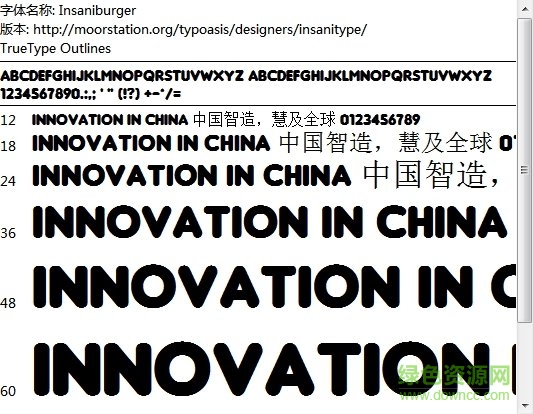
insaniburger字體是一款有著極佳視覺呈現(xiàn)的英文字體,自帶加粗加黑設(shè)計,讓英文文字更加深入人心,有著不錯的第一印象,給你的設(shè)計更加獨特光彩,喜歡的朋友就來綠色資源網(wǎng)收藏吧!
insaniburger字體給文字富裕了獨有的深沉和莊重之感,讓文字在第一時間能夠吸引讀者的注意,中文精簡大方,英文流暢穩(wěn)重,讓你的平面設(shè)計、包裝設(shè)計更有亮點。
本字體相關(guān)還有一款insaniburger with cheese字體,造型上十分可愛,可以使用在廣告創(chuàng)意、藝術(shù)設(shè)計等方面,感興趣的朋友可以看看!